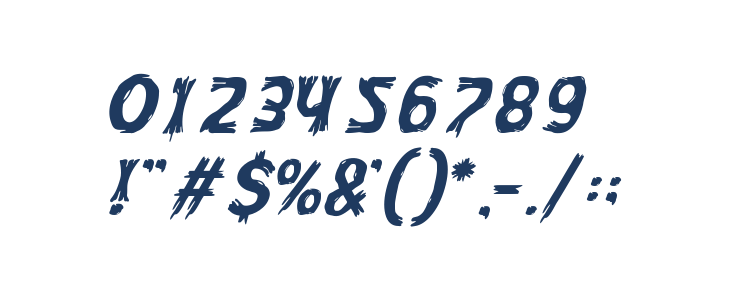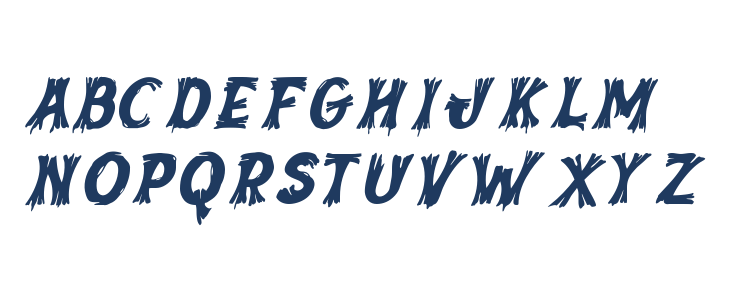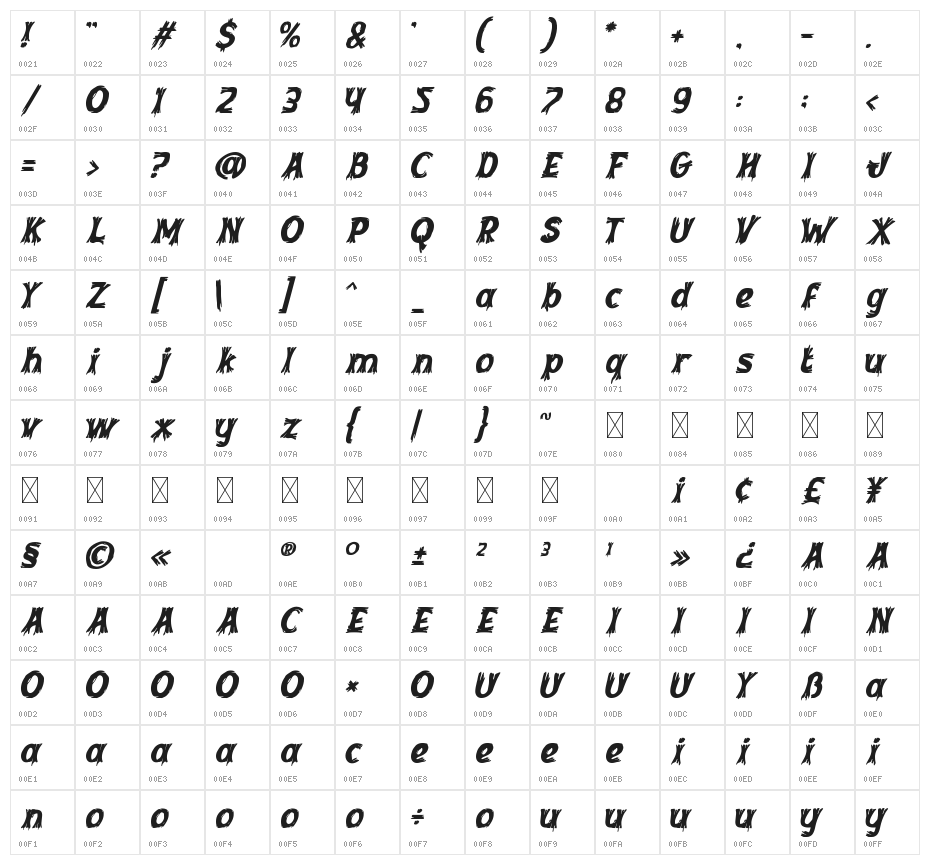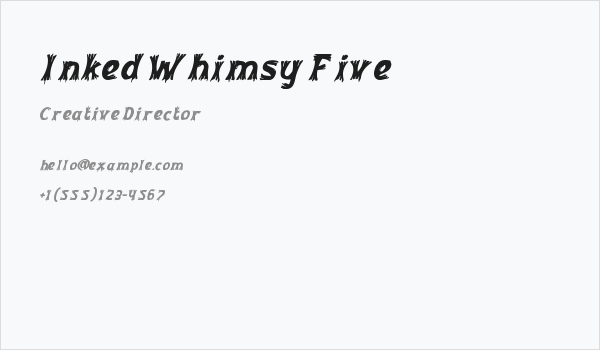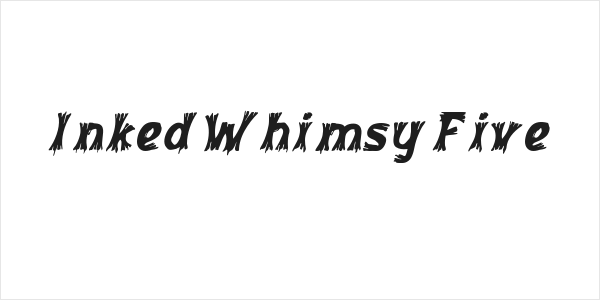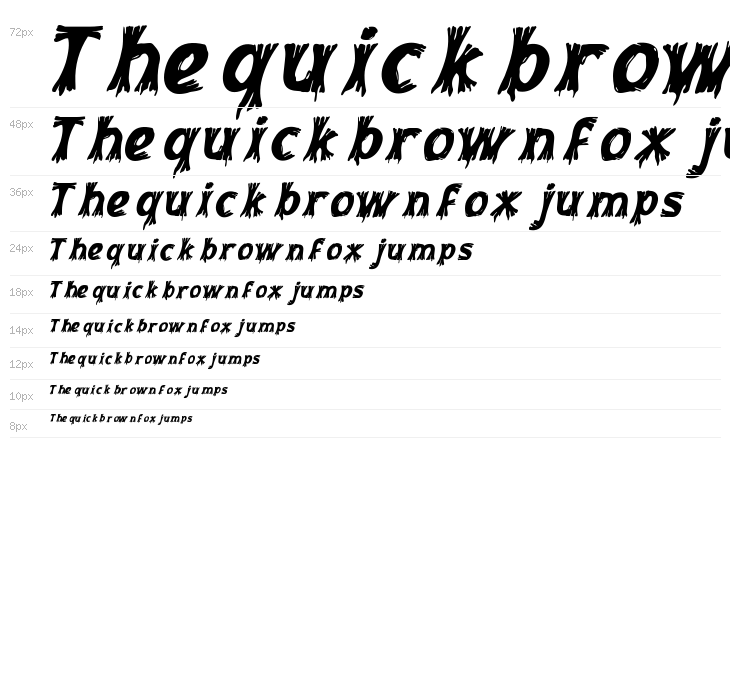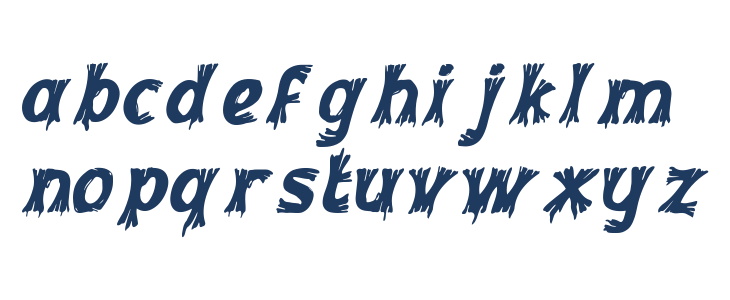
Inked Whimsy Five Font
| Larghezza | Expanded |
| Stile generale | Decorative, Whimsical, Playful |
| Caso d'uso | Headlines, Posters, Logos, Themed Graphics |
| Progetti proposti | Halloween posters, children's book covers, party invitations, comic titles, event flyers. |